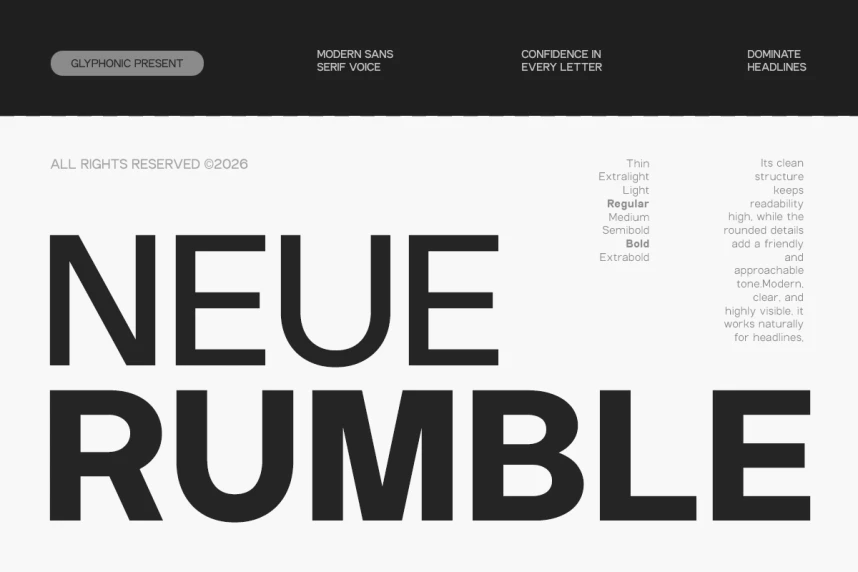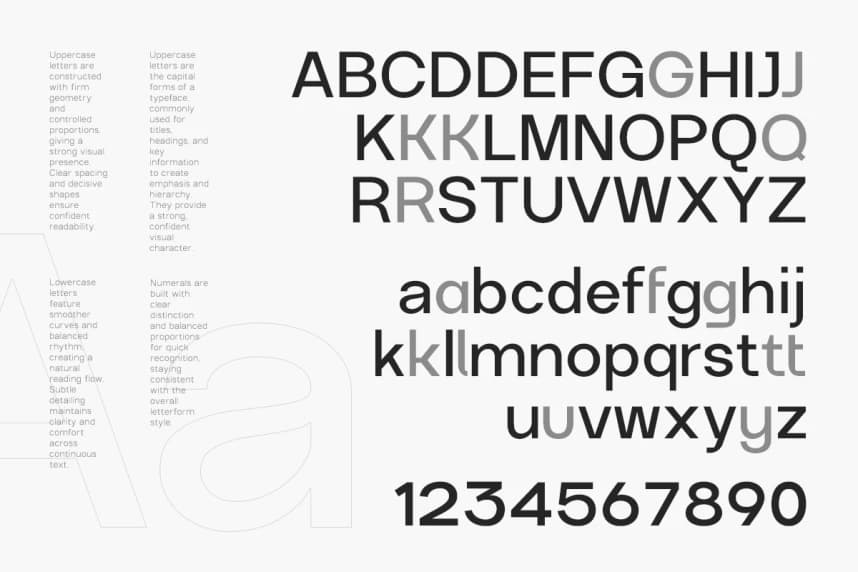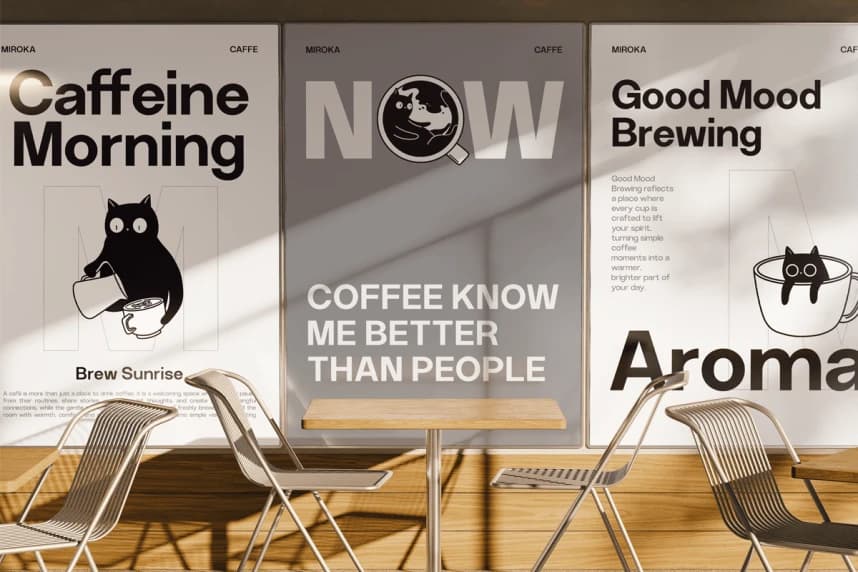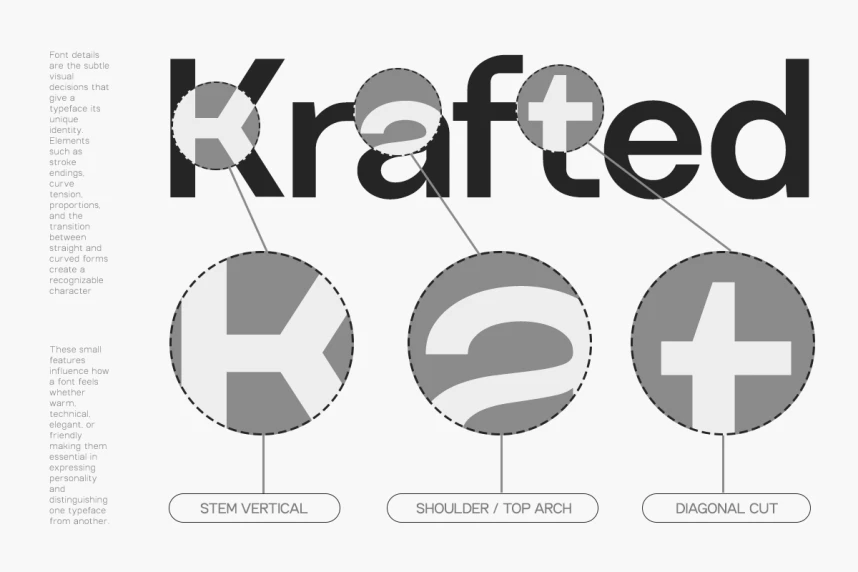
GC Neue Rumble – Modern Elegant Sans Font
GC Neue Rumble – Modern Elegant Sans Font, zarafeti modern netlikle birleştiren çağdaş bir sans-serif yazı tipidir. Dengeli oranlar ve sofistike ayrıntılarla tasarlanmış olan Neue Rumble, temiz ve zarif bir tipografik ifade sunar; bu ifade hem zamansız hem de ileri görüşlü bir his verir.
GC Neue Rumble – Modern Elegant Sans Font, çağdaş bir sans serif yazı tipidir ve rafine zarafet ile modern netliği birleştirir. Orantıları dengeli ve sofistike detaylarla tasarlanan Neue Rumble, temiz ve zarif bir tipografik ses sunar; bu ses hem zamansız hem de ileriye dönük hissedilir.